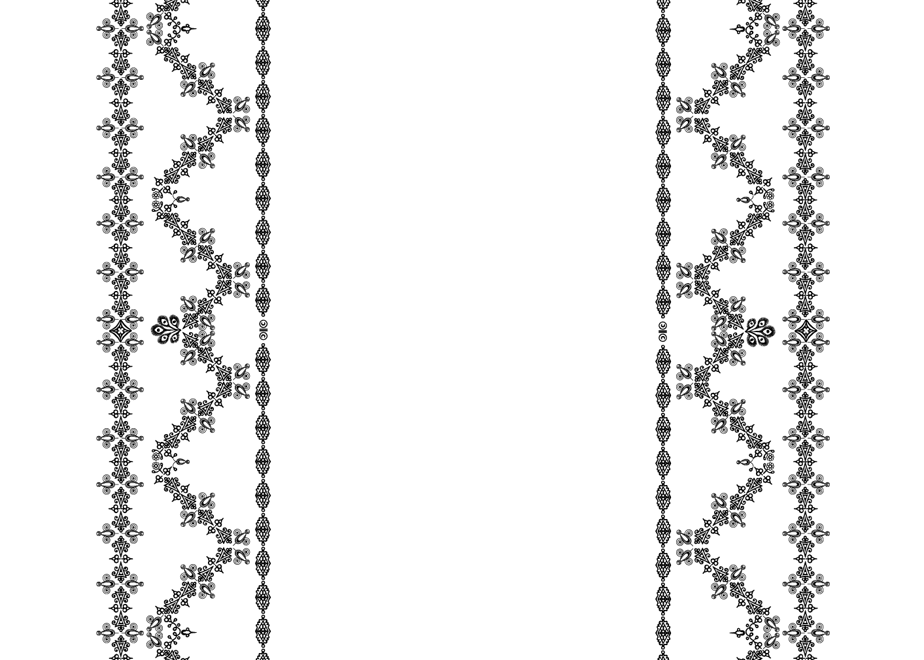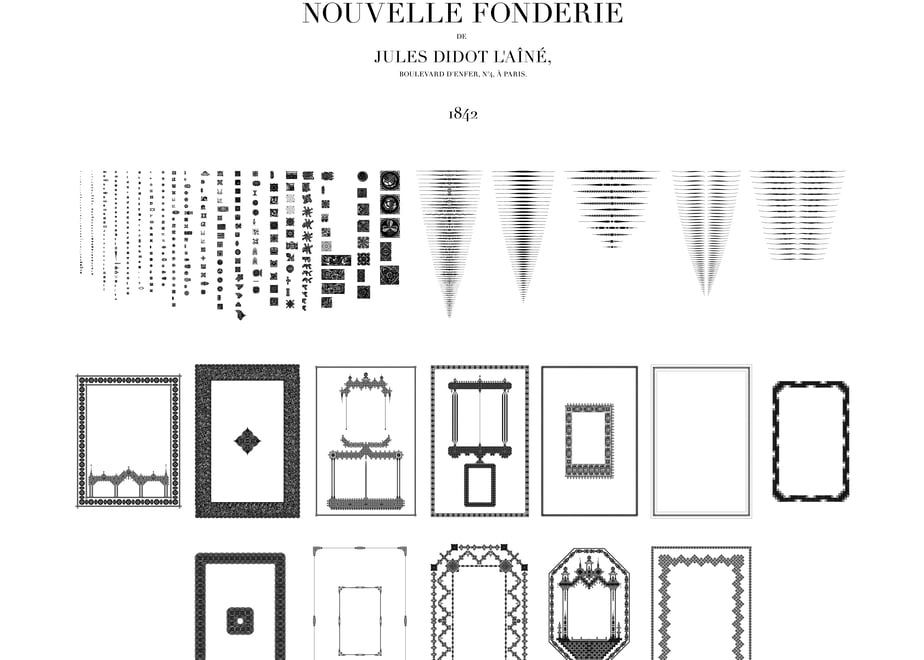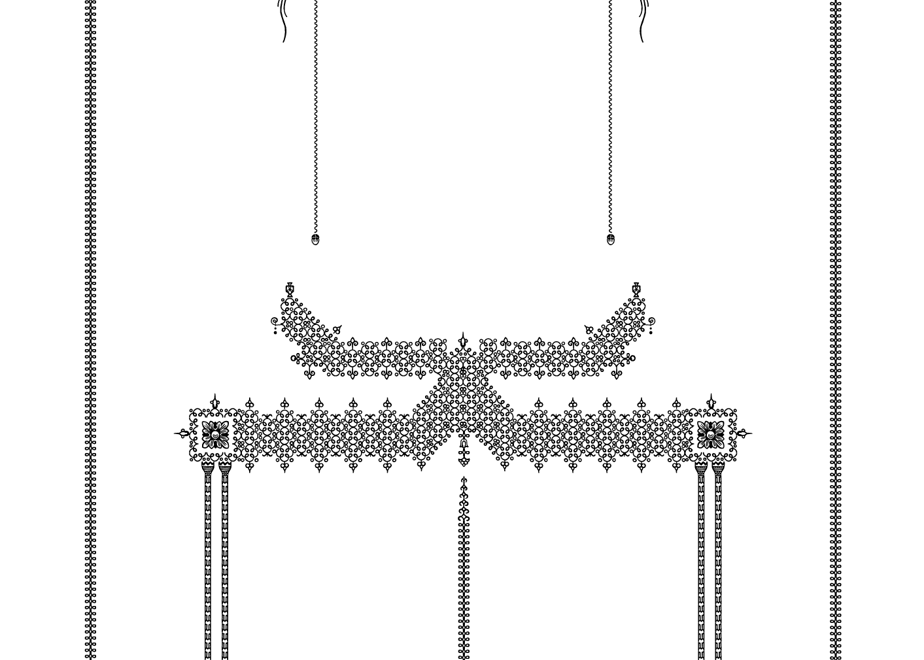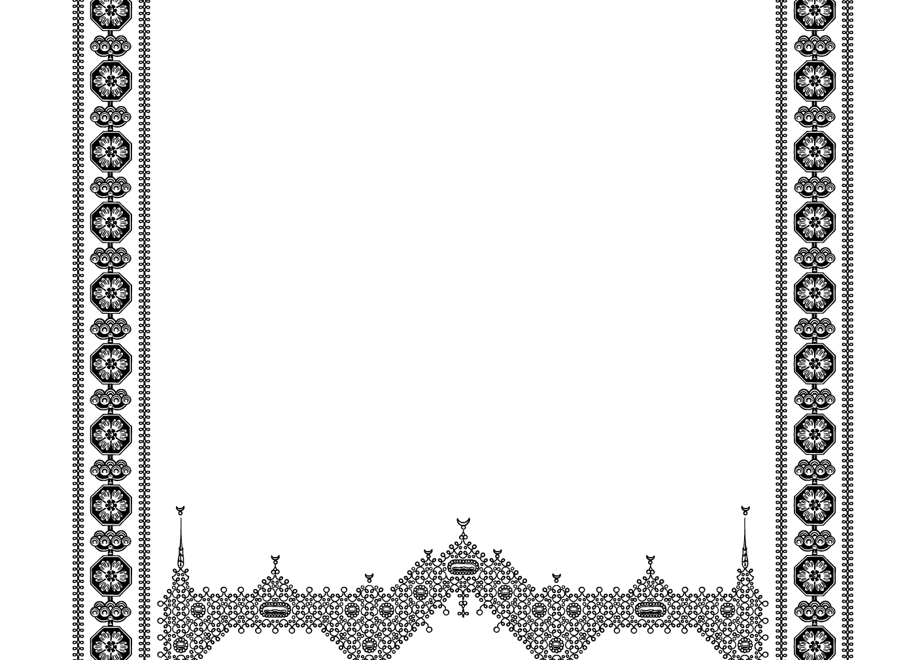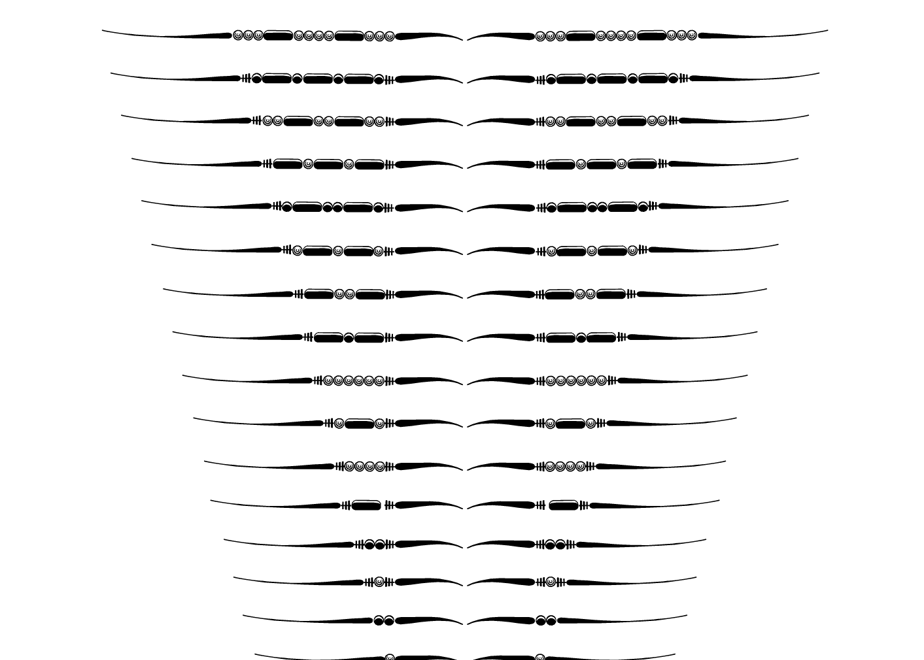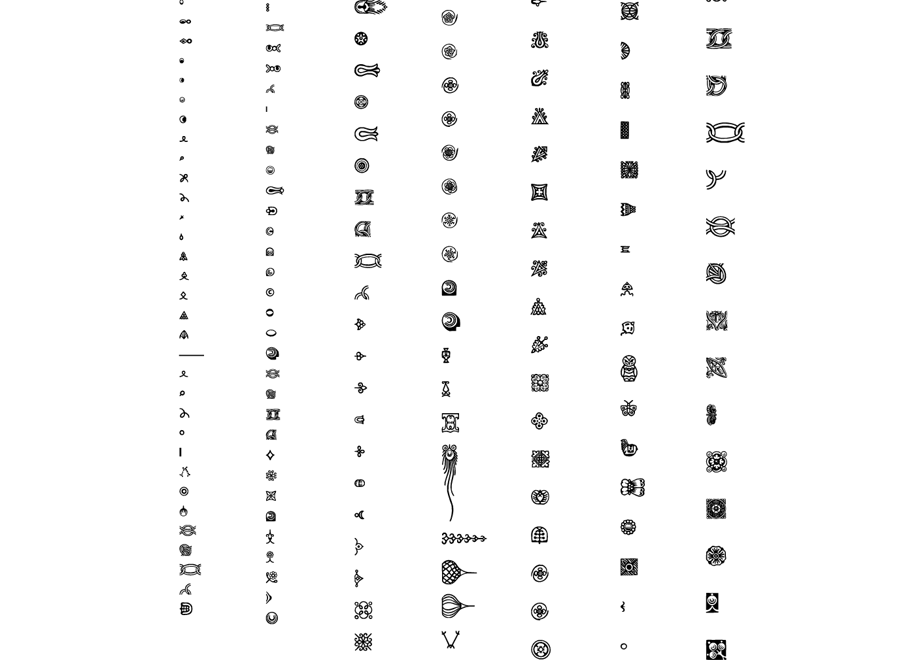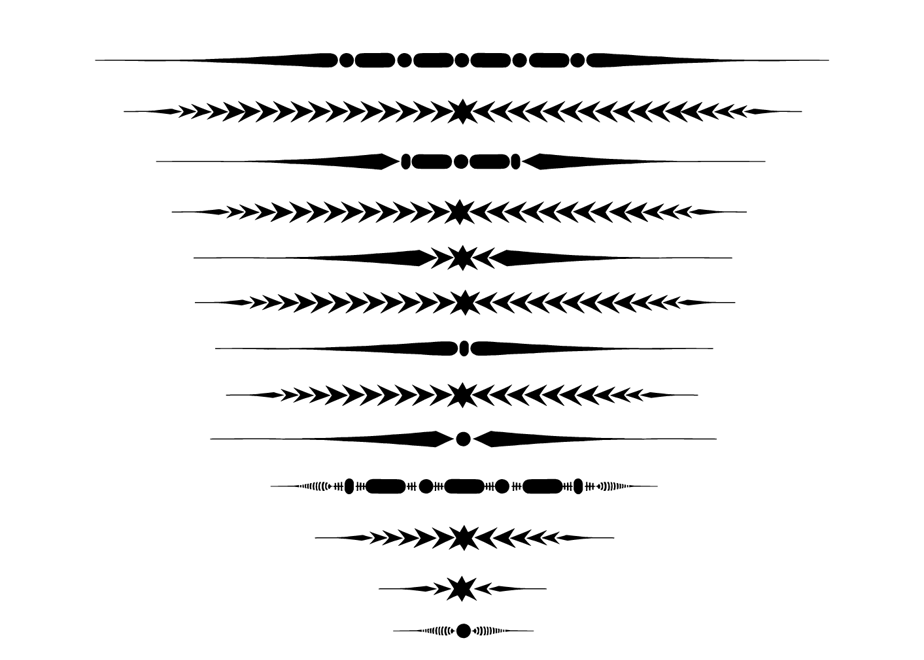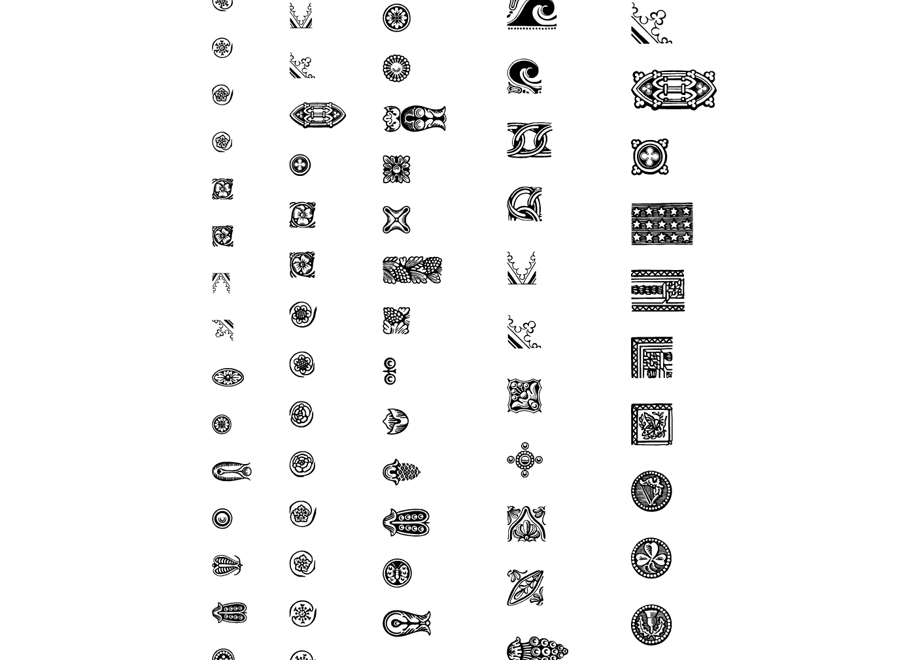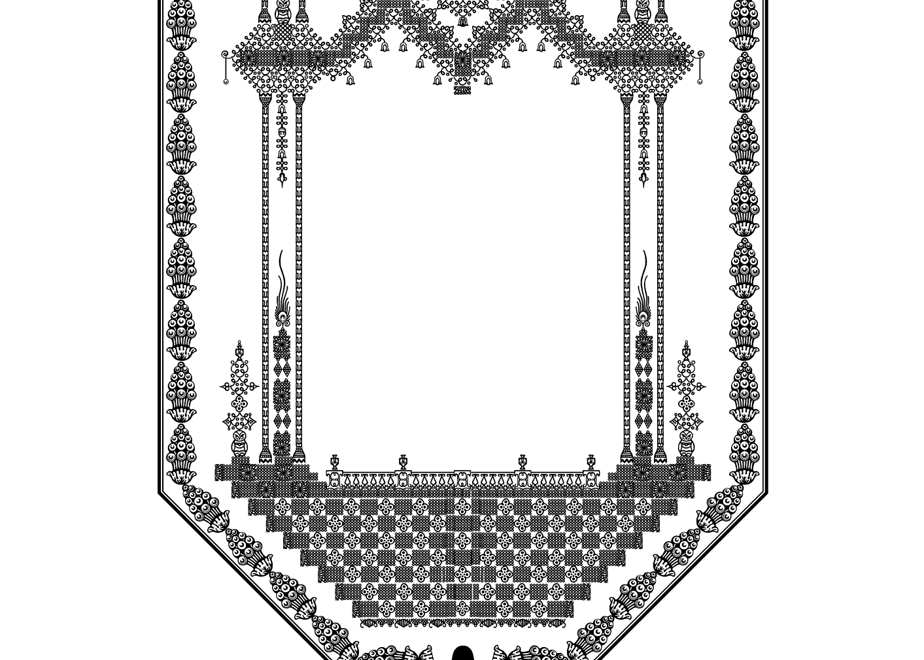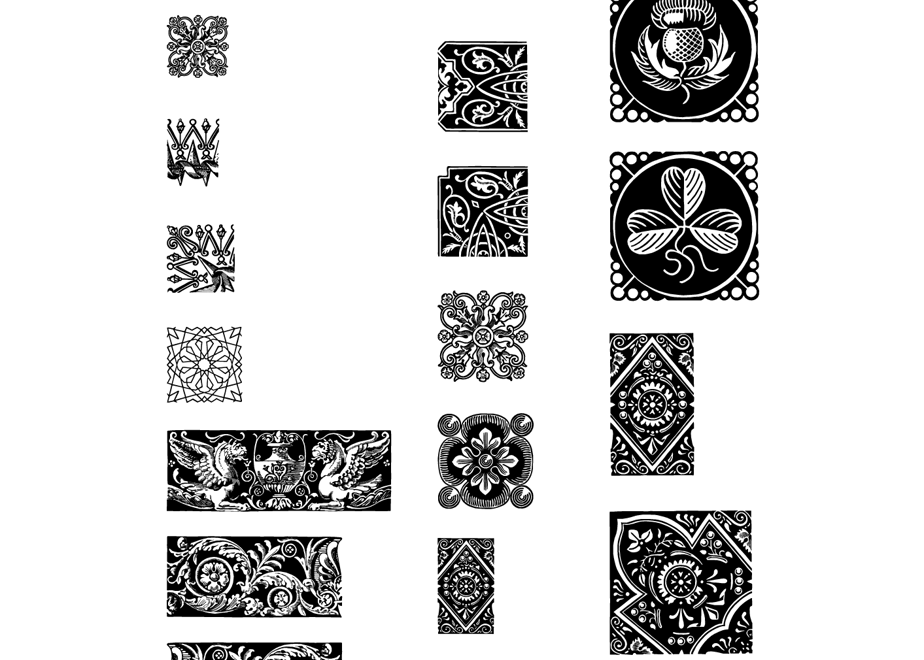
装飾活字【PNGエディション】SPÉCIMEN DE LA NOUVELLE FONDERIE DE JULES DIDOT(1842)
装飾活字:【PNG エディション】SPÉCIMEN DE JULES DIDOT(1842)
1842年に発行された Jules Didot の活字見本帳に収録された装飾活字および装飾罫線を、個別に分割した透過PNG形式で収録しています。